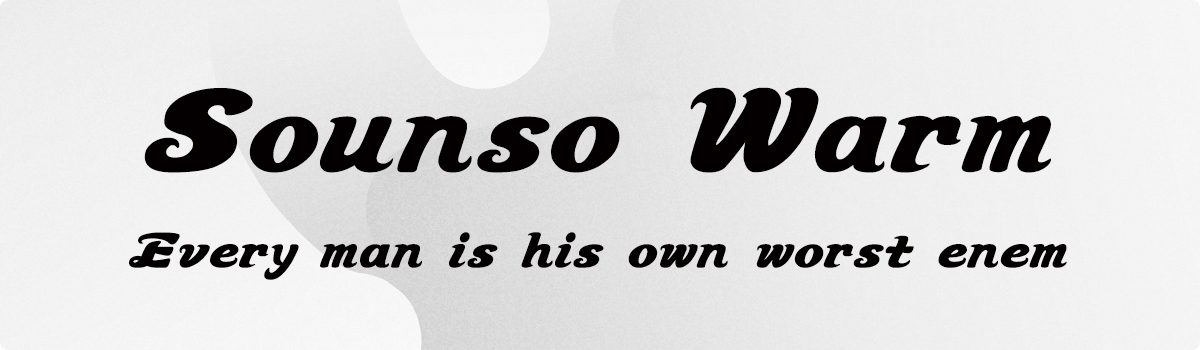
Sounso Warm
Sounso Warm,这款字体结构工整、笔画清晰,兼顾美观与易读性,适用于标题、正文、海报、包装、LOGO 等多种场景。字形优雅稳定,风格百搭耐看,适配日常排版与创意设计,让文字呈现更舒适、更具质感。Sounso Warm一笔一画,皆是细节,以均衡的比例、流畅的线条打造舒适视觉体验,字形端正大气,风格简约现代。无论是商业设计、品牌宣传还是日常排版,都能轻松驾驭,让文字更有格调与力量。Sounso Warm字体下载。